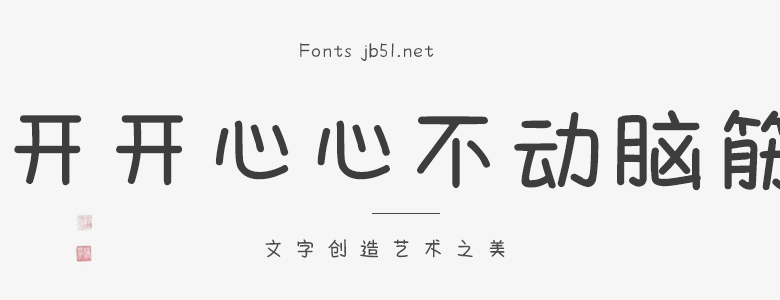
開(kāi)開(kāi)心心不動(dòng)腦筋字體是一款充滿樂(lè)趣和創(chuàng)意的字體設(shè)計(jì)。這款字體獨(dú)特的風(fēng)格,讓人一眼便能記住。它不僅具有鮮明的個(gè)性,而且非常適合用于歡樂(lè)、輕松、活潑的場(chǎng)合。 開(kāi)開(kāi)心心不動(dòng)腦筋字體的特點(diǎn)在于其獨(dú)特的曲線和飽滿的圓潤(rùn)感。每個(gè)字母的筆畫都呈現(xiàn)出一種歡樂(lè)的彎曲,像是在歡快地跳躍。字形設(shè)計(jì)上,盡量將每個(gè)字母的形狀簡(jiǎn)化,使得字體看起來(lái)既可愛(ài)又易于閱讀。同時(shí),字體的間距也經(jīng)過(guò)了精心的調(diào)整,使得文本整體看起來(lái)既不擁擠又不失活潑感。 這款字體的設(shè)計(jì)靈感來(lái)源于手寫字和兒童畫的風(fēng)格。筆畫線條自由流暢,沒(méi)有任何拘束,給人一種輕松愉悅的感覺(jué)。同時(shí),字體的筆畫設(shè)計(jì)得非常簡(jiǎn)潔,即使是初次使用的人也能很快掌握。 總的來(lái)說(shuō),開(kāi)開(kāi)心心不動(dòng)腦筋字體是一款充滿童趣和創(chuàng)意的字體。它不僅適合用于兒童用品、游戲、動(dòng)畫等場(chǎng)合,也可以用于一些輕松、歡快的文案和宣傳材料中。希望這款字體能為您的設(shè)計(jì)帶來(lái)新的靈感和活力。